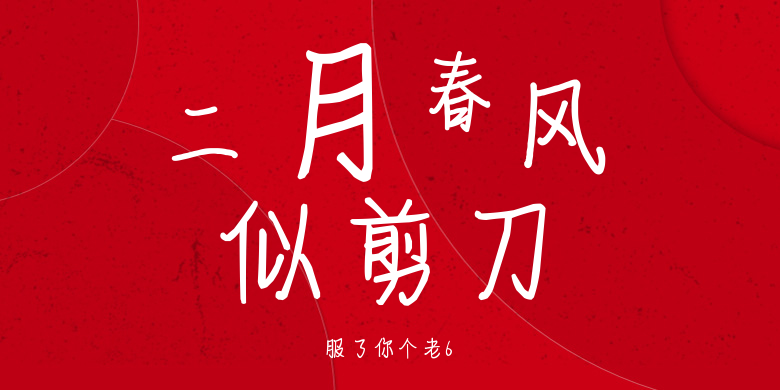
服了你个老6
服了你个老6,这款字体结构工整、笔画清晰,兼顾美观与易读性,适用于标题、正文、海报、包装、LOGO 等多种场景。字形优雅稳定,风格百搭耐看,适配日常排版与创意设计,让文字呈现更舒适、更具质感。服了你个老6一笔一画,皆是细节,以均衡的比例、流畅的线条打造舒适视觉体验,字形端正大气,风格简约现代。无论是商业设计、品牌宣传还是日常排版,都能轻松驾驭,让文字更有格调与力量。服了你个老6字体下载。